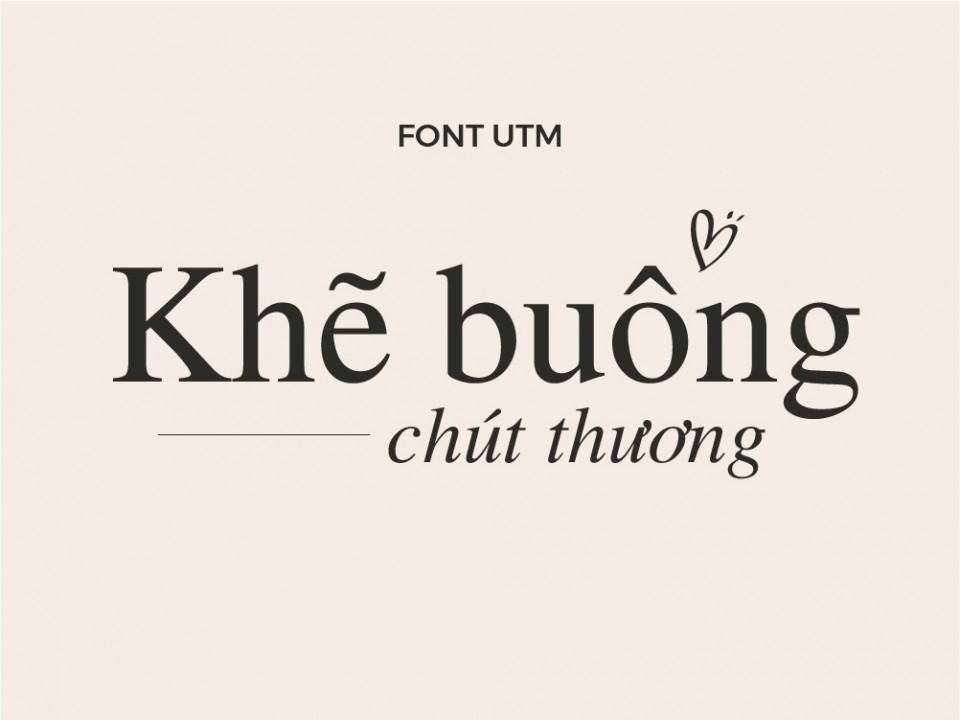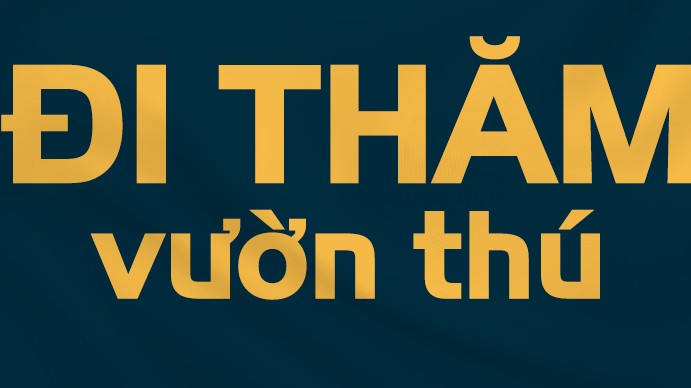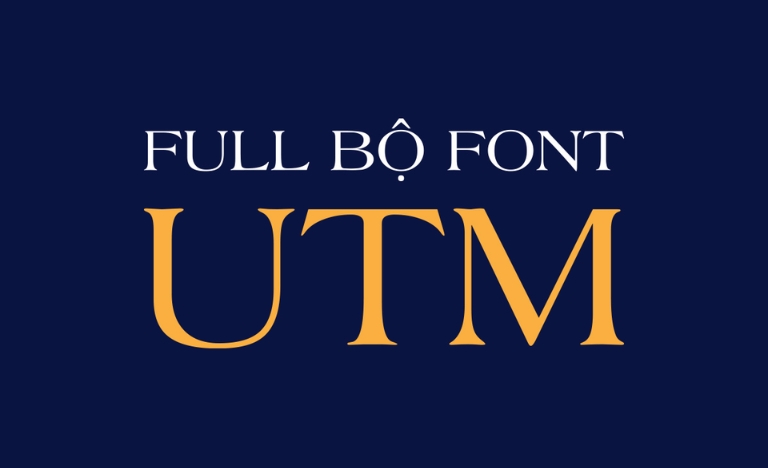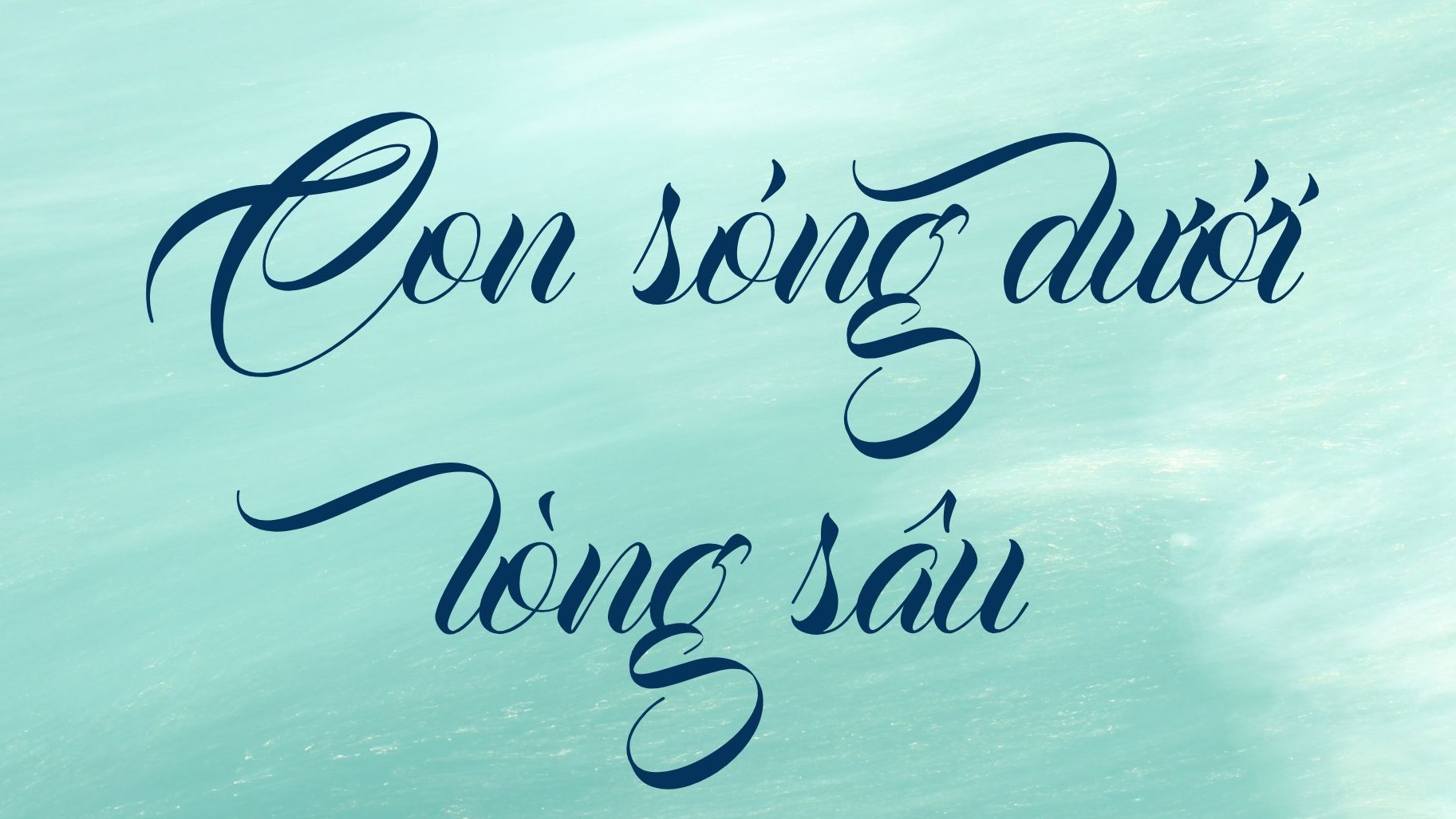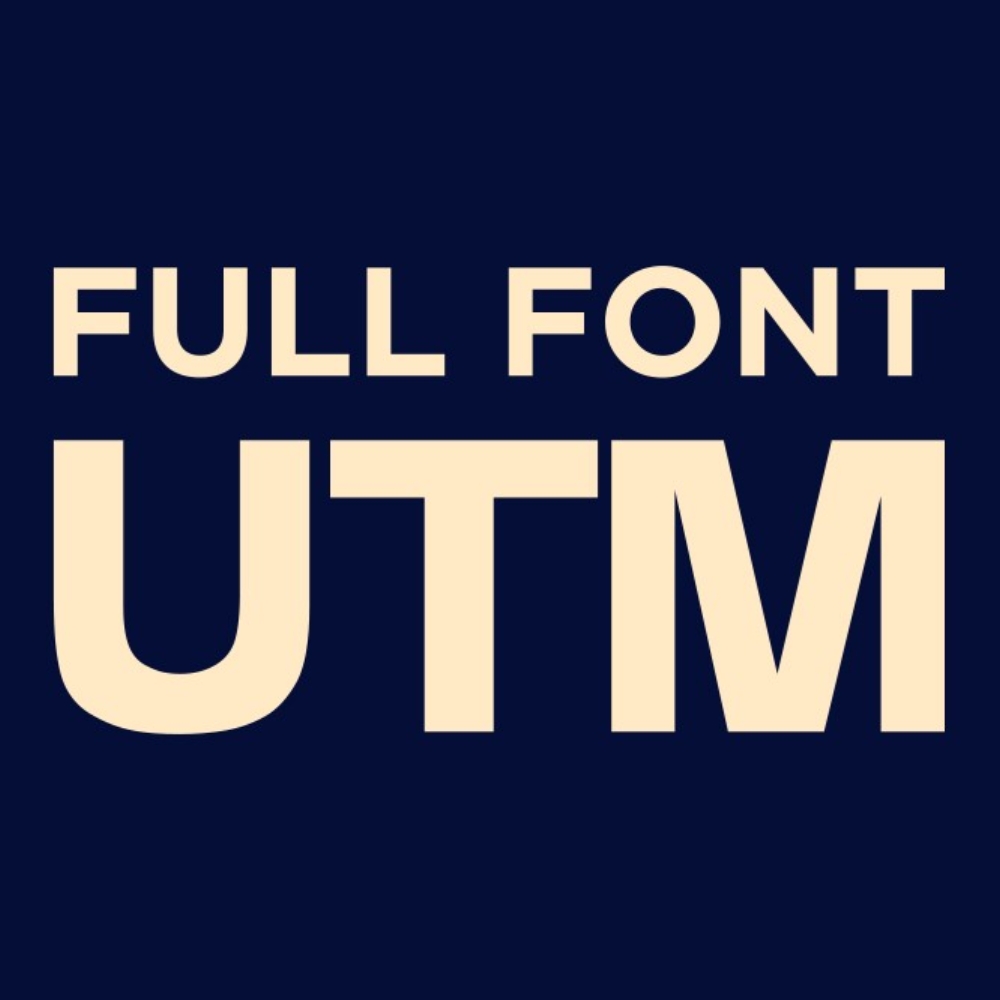
Bộ font UTM (Unicode Tiện Nghi) từ lâu đã trở thành một phần không thể thiếu trong kho tài nguyên của những người làm nghề thiết kế và kỹ thuật tại Việt Nam. Với ưu điểm hỗ trợ bảng mã Unicode chuẩn, việc tải font UTM giúp bạn loại bỏ hoàn toàn các lỗi hiển thị dấu thanh tiếng Việt, mang lại sự đồng bộ cho các bản hồ sơ thiết kế, bản vẽ CAD và ấn phẩm truyền thông.
Font UTM
Đặc điểm nổi bật của kho phông chữ UTM trong trình bày dự án
Điểm thu hút của dòng font này chính là sự phong phú về phong cách, từ những kiểu chữ không chân hiện đại đến các mẫu thư pháp nghệ thuật. Việc tải bộ font UTM cung cấp cho người dùng khả năng tùy biến cao cho từng hạng mục công việc cụ thể. Các ký tự được thiết kế với sự tỉ mỉ, giúp các dấu thanh như huyền, sắc, hỏi, ngã, nặng phối hợp cân đối với cấu trúc chữ gốc, tạo nên sự mạch lạc và tính thẩm mỹ cao cho văn bản.
Sự ổn định của hệ thống font UTM Việt hóa còn thể hiện qua khả năng hiển thị tương thích trên nhiều nền tảng phần mềm khác nhau. Dù bạn sử dụng để trình bày slide thuyết trình, soạn thảo hợp đồng xây dựng hay ghi chú trên các bản vẽ kỹ thuật phức tạp, các nét chữ vẫn giữ được độ sắc sảo và rõ ràng. Đây là lựa chọn hữu ích để thể hiện tư duy tổ chức thông tin khoa học và gu thẩm mỹ chuyên nghiệp cho mọi công trình.
| Dòng Font tiêu biểu | Đặc điểm thiết kế | Ứng dụng phù hợp |
| UTM Helve / Helvetins | Hiện đại, trung tính, dễ đọc | Ghi chú bản vẽ CAD, hồ sơ kỹ thuật |
| UTM Bebas / Impact | Nét dày, cao, gây chú ý mạnh | Tiêu đề Poster, bảng biển cảnh báo |
| UTM Thư pháp Thiên Ân | Mềm mại, mô phỏng nét cọ | Nhận diện thương hiệu Resort, Cafe |
| UTM Neo Sans Intel | Hình học tối giản, công nghệ | Website, Profile doanh nghiệp |
| UTM Aristote / Neutra | Thanh lịch, đậm chất kiến trúc | Bìa hồ sơ năng lực, Brochure |
03 Ứng dụng font UTM vào thực tế ngành xây dựng
Nhờ tính ứng dụng rộng rãi, việc sử dụng các mẫu chữ từ bộ tải font UTM Việt hóa mang lại giá trị thực tế cao trong quá trình triển khai dự án:
- Hệ thống biển báo công trường: Sử dụng tải font UTM Impact hoặc Bebas giúp các thông báo an toàn, chỉ dẫn khu vực thi công trở nên rõ nét, hỗ trợ công nhân và giám sát nắm bắt thông tin nhanh chóng từ khoảng cách xa.
- Nhận diện thương hiệu không gian nghỉ dưỡng: Việc tải font UTM thư pháp Thiên Ân là phương án hiệu quả để làm biển tên phòng hoặc menu tại các khu homestay container, nhà lắp ghép mang phong cách gần gũi với thiên nhiên, tạo dấu ấn văn hóa riêng.
- Trình bày thông số bản vẽ chuyên sâu: Sử dụng utm helvetins download font giúp các dòng chú thích về vật liệu panel, kết cấu khung thép trong AutoCAD trở nên minh bạch, chuyên nghiệp và hạn chế tình trạng nhầm lẫn số liệu.
04 Lưu ý để bố cục bộ font UTM chỉn chu trên hồ sơ thiết kế
Để khai thác hiệu quả vẻ đẹp của dòng font đa năng này, người thiết kế nên lưu tâm một số lưu ý kỹ thuật sau:
- Phân cấp thông tin bằng độ đậm: Bạn có thể phối hợp tải font utm swiss 721 black condensed cho các thông số quan trọng và dùng download font utm helve cho các đoạn mô tả để tạo ra sự tương phản thị giác, giúp người đọc dễ dàng theo dõi mạch logic.
- Lựa chọn kiểu chữ phù hợp với vật liệu: Khi thiết kế cắt chữ nổi laser trên inox hoặc gỗ cho nhà lắp ghép, hãy ưu tiên các font có cấu trúc chắc chắn như download font utm neutra để đảm bảo độ bền và độ sắc nét sau khi gia công.
- Kiểm soát khoảng cách dòng: Đối với các font có chân hoặc thư pháp như download font utm thuphap thien an, bạn nên để khoảng cách dòng thoáng hơn một chút để các nét uốn lượn không bị chồng lấn, giữ được sự thanh thoát cho văn bản.